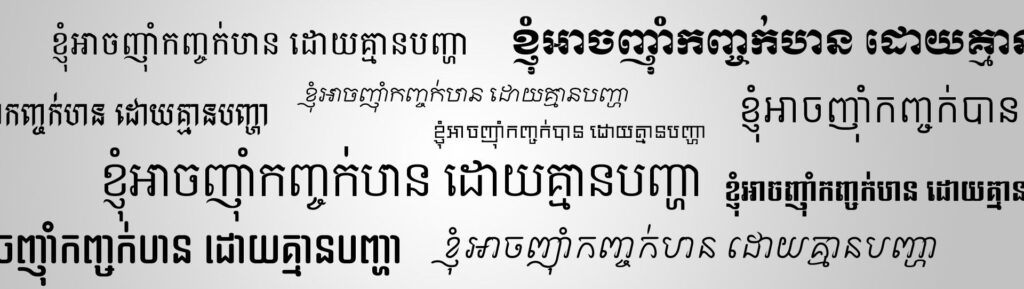
Trong các dự án thiết kế đa quốc gia hoặc các công trình có yếu tố văn hóa đặc thù, việc sử dụng đúng bộ chữ bản địa đóng vai trò then chốt để truyền tải thông tin chính xác. Việc download font Khmer giúp các kiến trúc sư và nhà thiết kế trình bày các bản vẽ kỹ thuật, biển chỉ dẫn hoặc hồ sơ dự án liên quan đến khu vực Campuchia một cách chuyên nghiệp.
Đặc trưng thẩm mỹ và cấu trúc của phông chữ Khmer Unicode
Điểm lôi cuốn đặc trưng của phông chữ Khmer nằm ở những đường nét uốn lượn tinh xảo, phản ánh đậm nét tinh hoa nghệ thuật và văn hóa Á Đông. Khi thực hiện tải font Khmer Unicode, người dùng sẽ nhận thấy cấu trúc các ký tự được thiết kế với độ chi tiết cao, các nét móc và phụ âm được sắp xếp theo nhịp điệu riêng biệt. Việc sử dụng bảng mã Unicode chuẩn giúp các ký tự hiển thị đồng bộ trên mọi nền tảng, đảm bảo văn bản không bị lỗi “ô vuông” hay nhảy nét khi chuyển đổi file giữa các phần mềm thiết kế.
Sự chuyên nghiệp của bộ chữ này còn thể hiện qua khả năng thích ứng linh hoạt. Dù được ứng dụng trên các văn bản thuyết minh dự án hay in ấn trên các vật liệu xây dựng thực tế như biển hiệu gỗ, kim loại, phông chữ vẫn giữ được vẻ thanh thoát và sang trọng. Đây là phương án hiệu quả để thể hiện sự am hiểu và tôn trọng văn hóa bản địa, giúp nâng cao giá trị thẩm mỹ cho các sản phẩm sáng tạo trong lĩnh vực kiến trúc và đời sống.
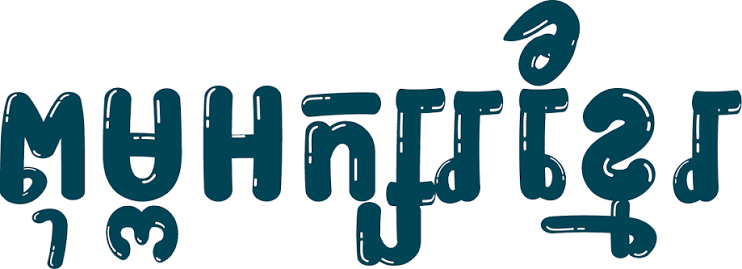
Thông tin kỹ thuật và tải font chữ Khmer Unicode trọn bộ
| Phân loại phong cách | Khmer Script / Traditional / Modern |
| Bảng mã hỗ trợ | Unicode chuẩn toàn cầu |
| Mục đích phù hợp | Bản vẽ CAD, Biển tên phòng, Brochure văn hóa |
Gợi ý trình bày: Ký tự Khmer thường có chiều cao lớn và nhiều nét chi tiết. Khi thiết kế, bạn nên phối hợp phông chữ này với một kiểu Sans-serif hiện đại cho các phần ghi chú số liệu để tạo sự cân bằng và giúp bố cục thông tin trở nên minh bạch hơn.
03 Ứng dụng phông chữ Khmer vào thực tế xây dựng
Nhờ vẻ ngoài giàu tính thẩm mỹ và sự chuẩn mực, việc sử dụng các kiểu chữ từ tải font Khmer mang lại giá trị thực tế cao trong quá trình triển khai dự án:
- Hệ thống biển chỉ dẫn cho khu nghỉ dưỡng: Tại các khu homestay container hoặc nhà lắp ghép hướng đến du khách quốc tế, sử dụng phông chữ Khmer cho biển tên phòng, bảng nội quy giúp tạo ấn tượng về sự chuyên nghiệp và thân thiện với văn hóa địa phương.
- Hồ sơ dự án và tài liệu thuyết minh: Sử dụng tải font chữ Khmer Unicode giúp các trang hồ sơ năng lực (Profile) phục vụ cho các đối tác tại thị trường Campuchia trở nên mạch lạc, thể hiện sự chỉn chu và năng lực của đơn vị thi công.
- Ghi chú kỹ thuật trên bản vẽ chuyên ngành: Độ sắc sảo của phông chữ hỗ trợ đắc lực cho kỹ sư khi trình bày các chỉ dẫn vật liệu panel, kết cấu khung thép trong các dự án xuất khẩu hoặc thi công tại nước bạn.
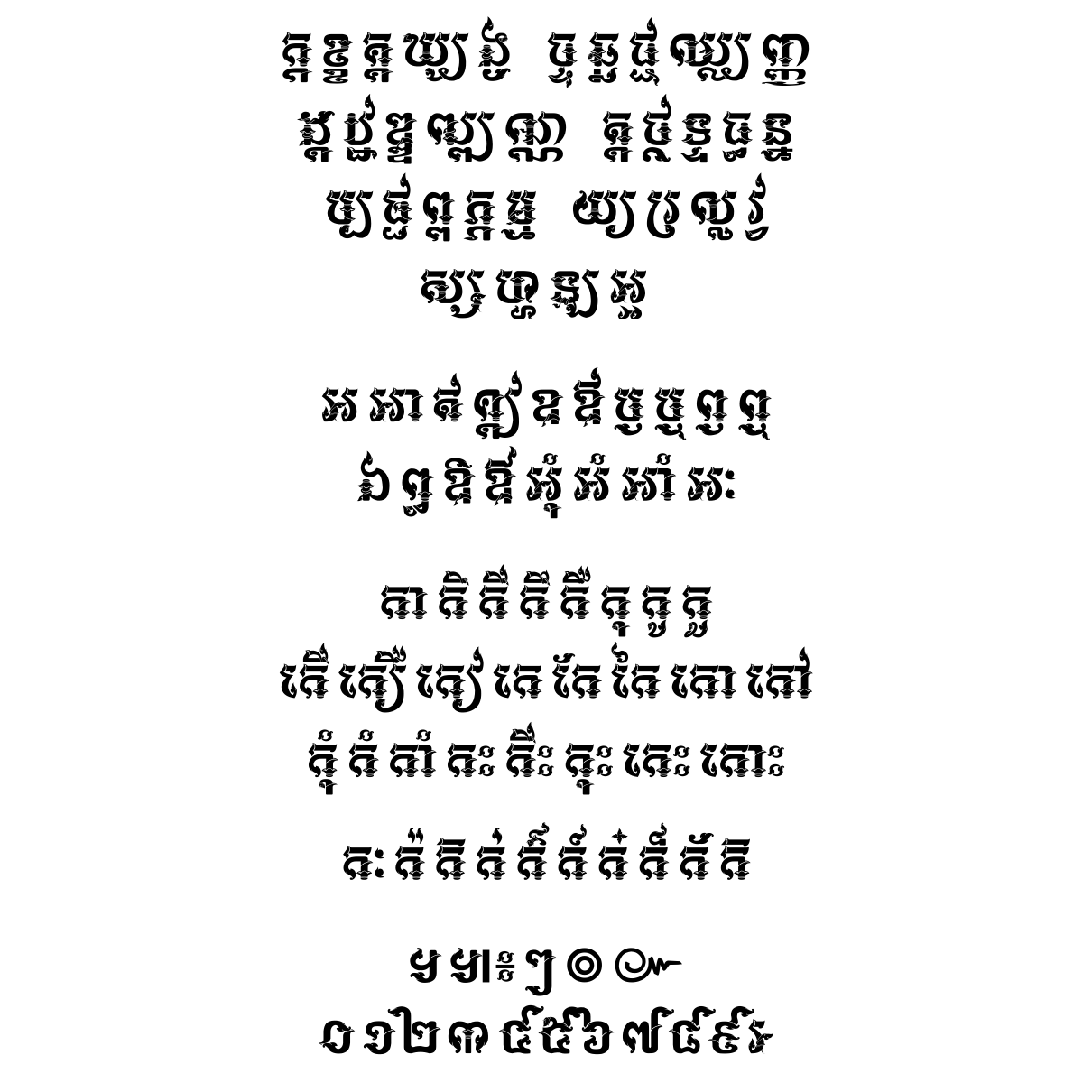
03 Lưu ý để bố cục phông chữ Khmer đạt độ sắc nét cao
Để khai thác hiệu quả vẻ đẹp nghệ thuật và tính năng đa năng của bộ phông này, người thiết kế nên lưu tâm một số kinh nghiệm kỹ thuật sau:
- Kiểm soát khoảng cách dòng (Leading): Do chữ Khmer có cấu trúc xếp tầng (chân chữ và dấu phụ bên trên), bạn nên nới rộng khoảng cách dòng thoáng hơn so với phông chữ Latinh để các ký tự không bị chồng lấn, giữ được sự rõ ràng khi đọc.
- Lựa chọn kích thước hiển thị: Phông chữ này hiển thị tốt ở kích thước trung bình trở lên. Với các ghi chú nhỏ trên bản vẽ CAD, bạn nên kiểm tra kỹ độ dày nét để đảm bảo các chi tiết nhỏ của chữ không bị mất đi khi in ấn trên khổ giấy lớn.
- Đồng bộ hóa bảng mã: Hãy luôn ưu tiên sử dụng khmer unicode thay cho các bảng mã cũ để đảm bảo tính tương thích khi gửi file hồ sơ thiết kế cho các bên liên quan, tránh tình trạng nhảy chữ không mong muốn.